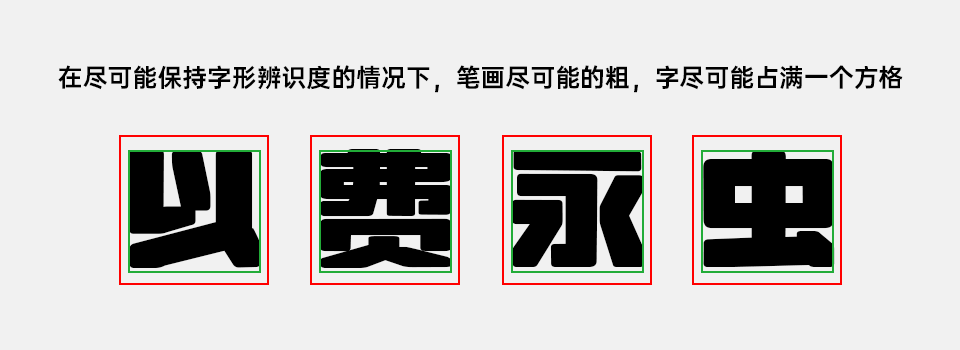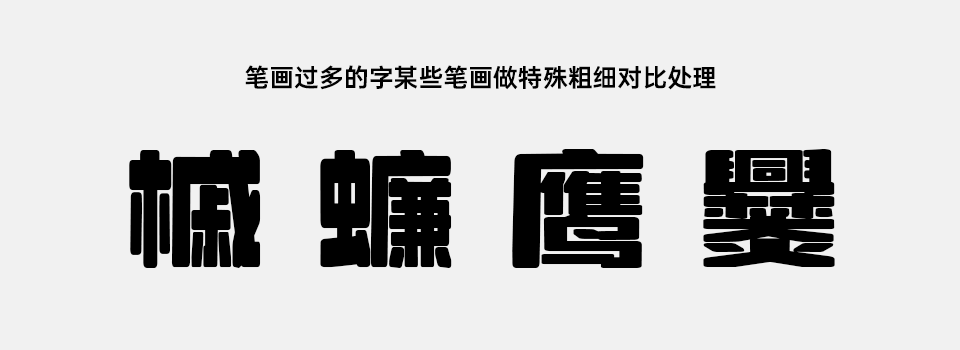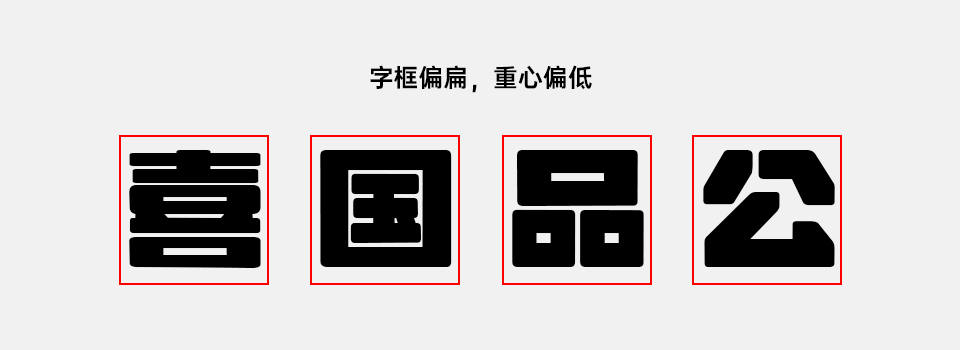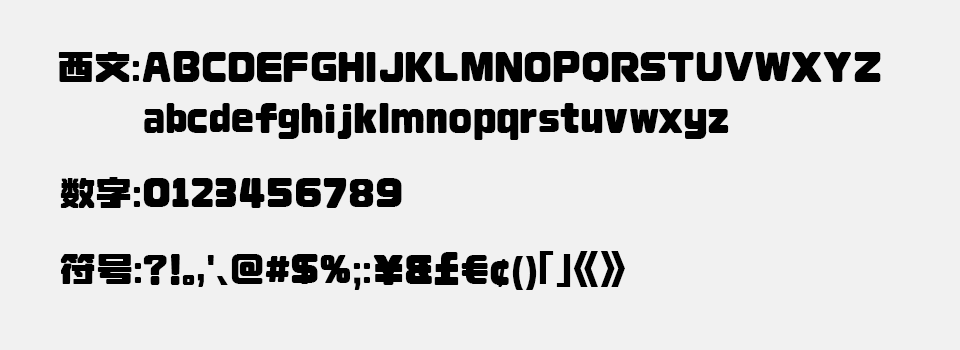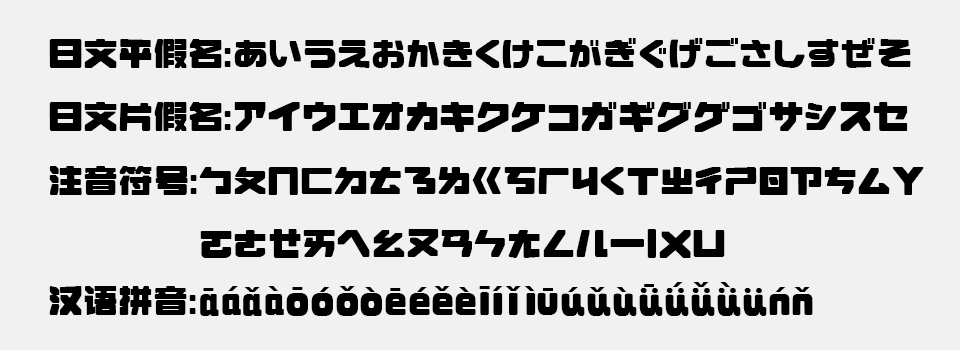
2020年突如其来的疫情,让我想创作一套属于自己的字体的愿望从遥不可及的理想变成了触手可及的现实。总想着这套字体一定要是在大街上随处可以见到的那种风格。什么样的字体最受欢迎?经过我个人的仔细观察,发现还是粗的类综艺黑体的美术字最受欢迎,这类字体总能在第一时间抓住人的眼球。于是我就按照自己的想法绘制了一种尽可能占满一个偏扁的长方形的粗黑字,没想到从去年年初到现在一年多的时间居然还把将近7000字的完整版做完了。
一开始的字体风格还不想现在这样,圆角是后来逐渐加上去的,我想要一种增加字体趣味性但是又不要看起来很像叠圆体之类的圆体美术体,于是就形成了如今的圆角。
理想的设计用途:该字体非常适合店招、房地产广告、地铁公交站广告海报、线上及线下的各类产品宣传、个人VLOG封面标题字体等。
字体特点
在尽可能保持字形辨识度的情况下,笔画尽可能的粗,字尽可能占满一个方格
笔画过多的字某些笔画做特殊粗细对比处理
字框偏扁,重心偏低
包含了西文、数字、符号、日文平假名、日文片假名、注音符号、汉语拼音等